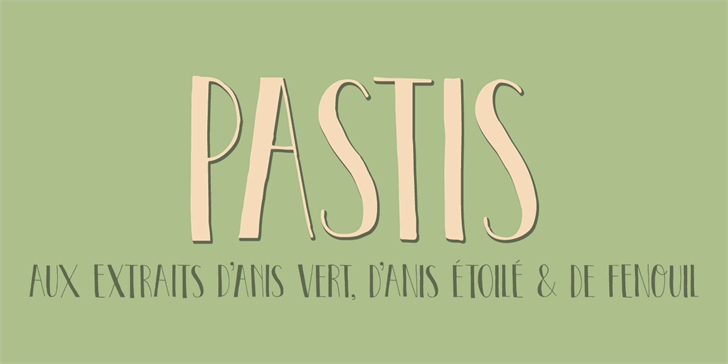
A fonte DK Pastis foi criada pelo designer Hamilton para uma estética retro elegante. Suas linhas leves e detalhes sutis criam um estilo que vai bem com qualquer projeto de design, seja para a web ou impressão. Ideal para aplicar em logomarcas, títulos de livros, posters e até mesmo designs gráficos para jogos e software. Com seu uso restrito apenas para fins pessoais, DK Pastis oferece uma versão gratuita para quem deseja experimentar antes de investir mais. Para uso comercial, o designer recomenda a compra da versão completa, que inclui ajustes de espaçamento entre caracteres (kerning), direitos de incorporação e todas as letras e extras disponíveis em seu site: hanodedfonts.com. Hamilton não permite a utilização desta fonte em jogos, aplicativos ou software. Para obter um licenciamento para esses usos, os usuários devem adquirir uma licença diretamente do site do designer. Além disso, há um arquivo FAQ incluído no zip que explica as condições de uso detalhadamente. A fonte DK Pastis é perfeita para designers gráficos e estilistas de nomes que procuram um estilo retro moderno para seus projetos. Ela combina com uma variedade de formatos, tornando-a uma opção muito valorizada no universo dos designs digitais.